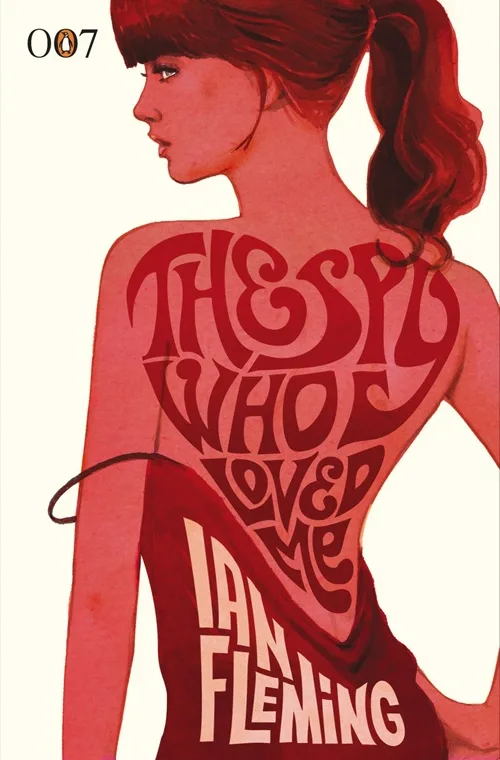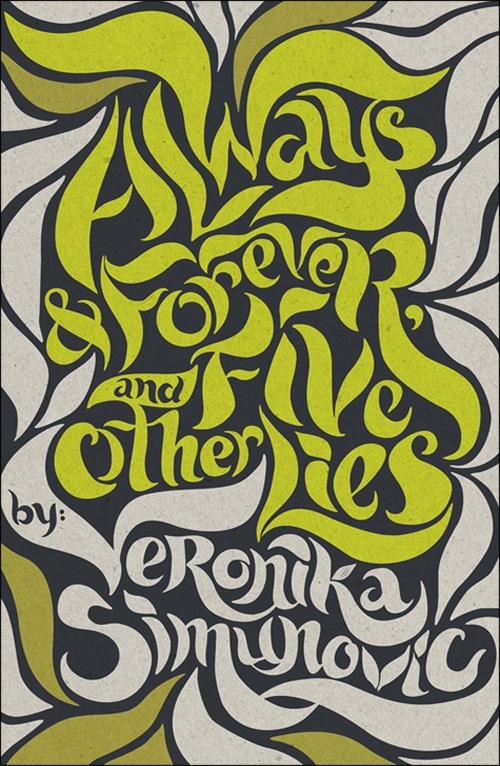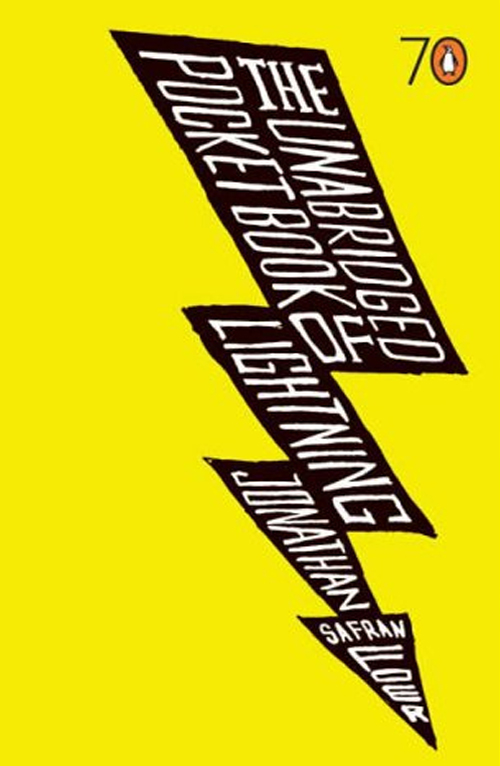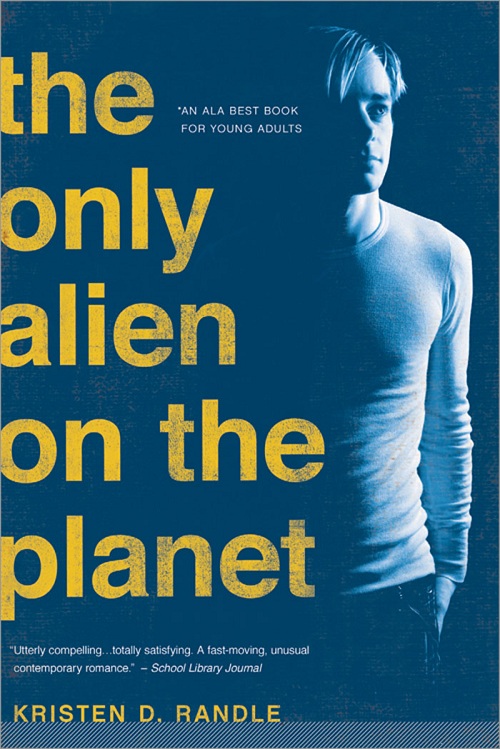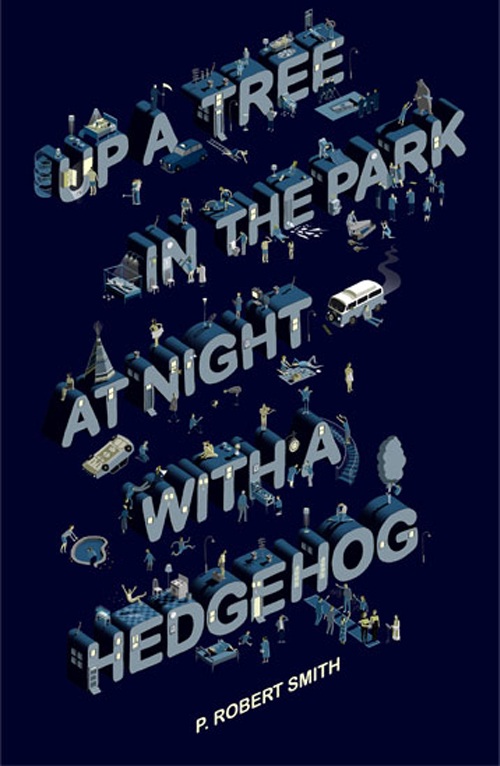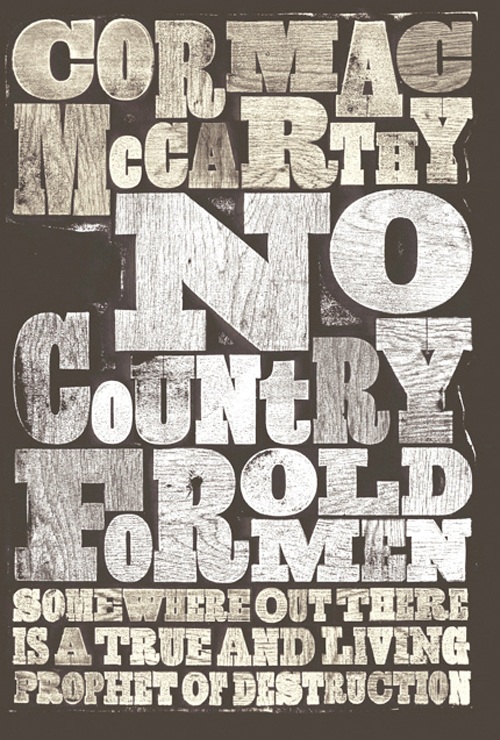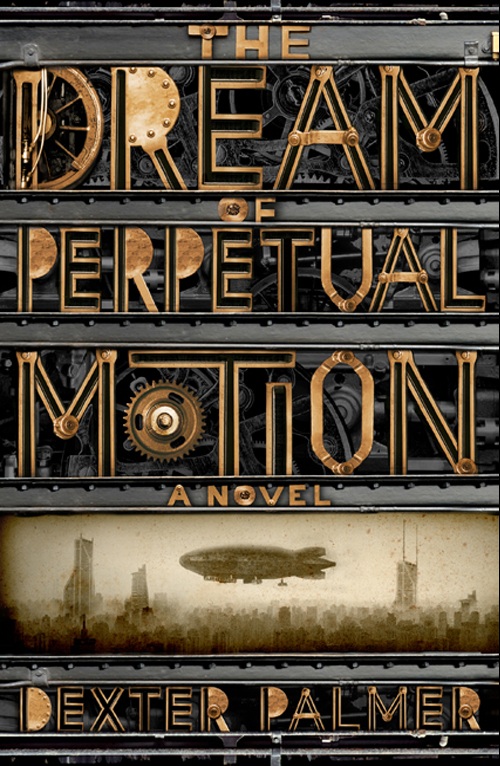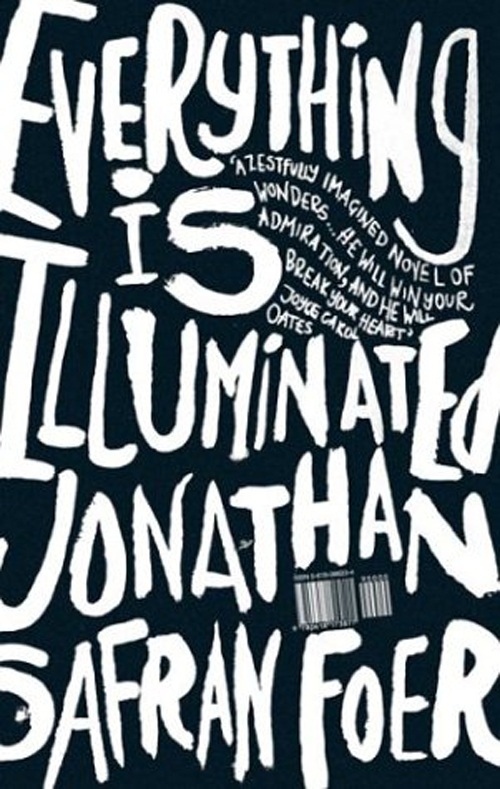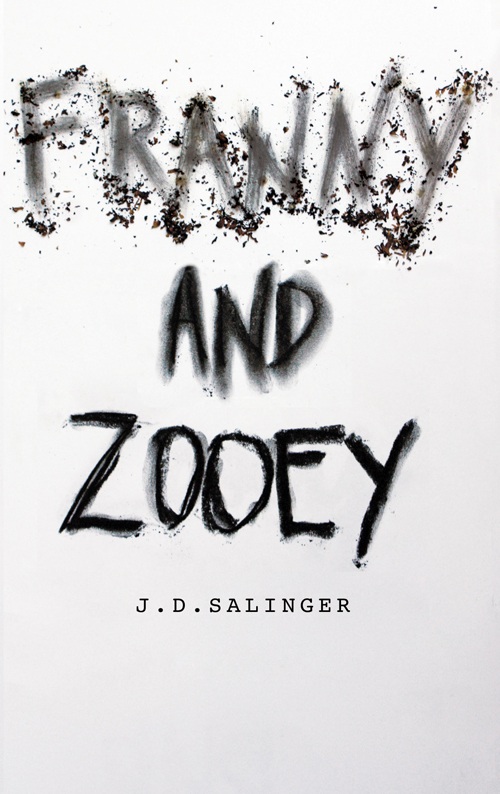
35 belas tipografias em capas de livros
Tipografia em capas de livros, belas artes tipográficas feitas nas capas de livros por designers de todo o mundo. (32)
Olhe como o bom uso e com muita criatividade nós podemos fazer com que a tipografia da capa de um livro fique belíssima, veja o trabalho destes designers que conseguem facilmente substituir a imagem da capa dos livros pela sua bela arte tipográfica.